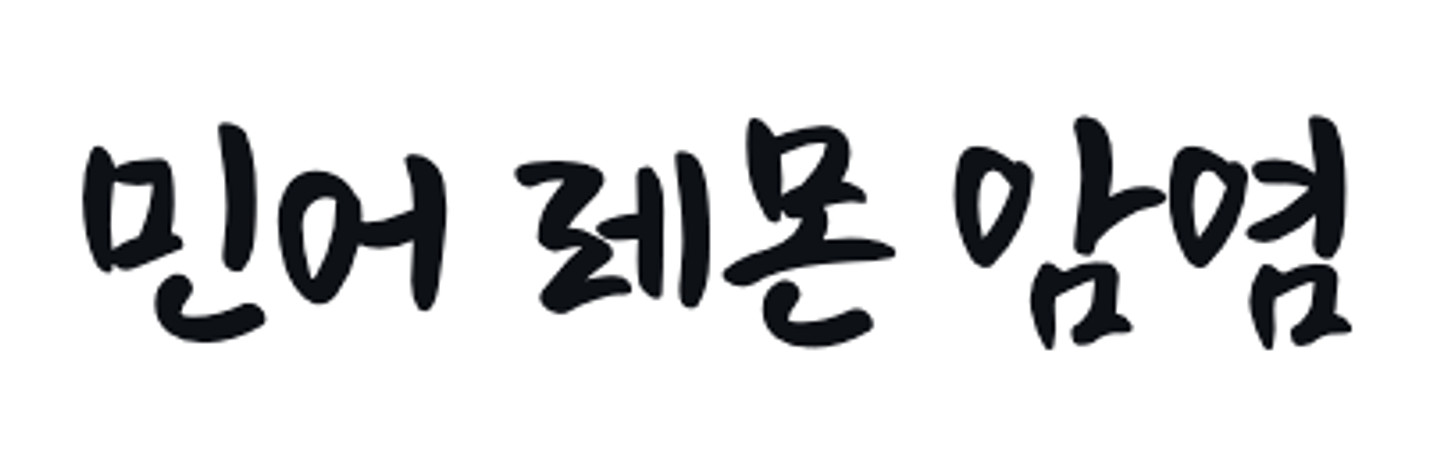
인터넷 돌아다니다가 폰트가 예뻐서 캡처한 짤입니다. (원본은 식당 메뉴판을 찍은 사진입니다) 산돌폰트검색에서도 찾아보고, 나름대로 시간을 들여 찾아봤는데 답을 찾지 못했습니다. 아무래도 필기체라서 찾기가 좀 더 어려운듯 합니다. 혹시 아시는 분 계시면 답변 부탁드립니다. 감사합니다.
밀양영남루체 밀양시